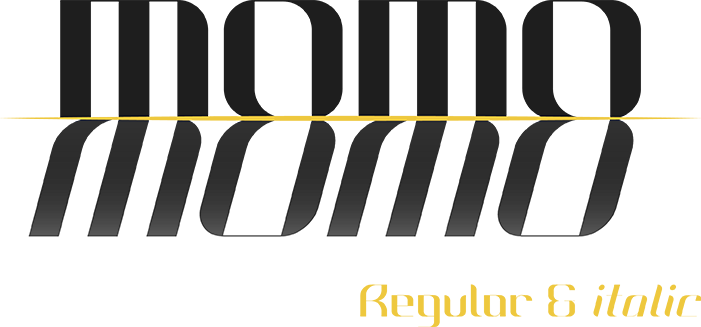
A família de fontes ‘Momo Typeface’ é uma escolha ideal para projetos que exigem notoriedade visível sem comprometer a legibilidade. Suas linhas carregadas e finas criam um contraste vibrante, iluminando o texto com profundidade e destaque. Com seu traço fino perfeitamente explorado ao limite perceptível da visão humana, esta fonte se destaca não apenas como uma opção de estilo, mas também como uma ferramenta única para destacar mensagens breves ou criar logotipos impactantes. Suas propriedades tornam a ‘Momo Typeface’ especialmente útil e divertida em aplicações onde o texto é breve ou os títulos devem ser chamativos, garantindo que a leitura seja clara independentemente do tamanho da fonte utilizada.